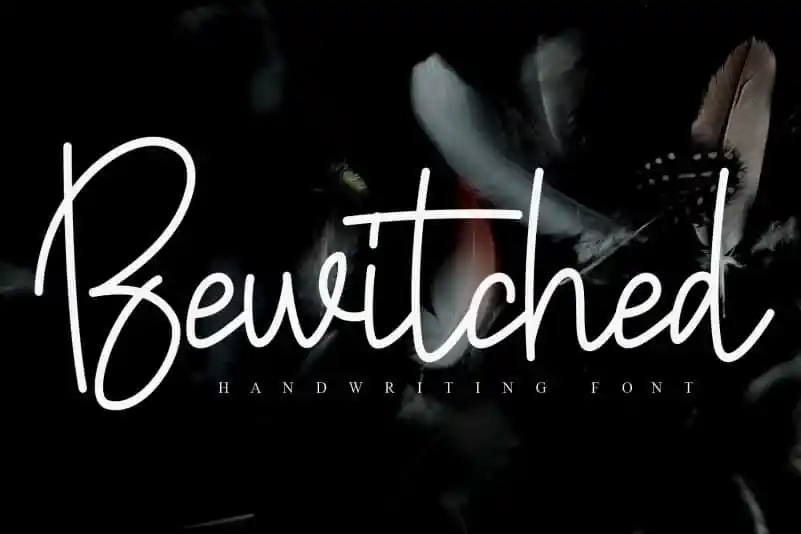
Bewitched Handwritten Font – Download Grátis
Descrição: Através do Bewitched Handwritten Font, a designer creativeletter oferece uma experiência única que vai além das típicas ferramentas de texto padrão. Esta fonte criada sob medida para escrita à mão é não apenas versátil e fácil de usar, mas também capaz de transformar qualquer documento em algo especial e personalizado. Com detalhes cuidadosamente projetados e uma aparente essência única, a Bewitched Handwritten Font traz vida ao seu conteúdo, permitindo que você expressa emoções e sentimentos de formas não tão triviais quanto o uso padrão do texto. Seja para um projeto editorial especial ou apenas para decorar textos pessoais, esta fonte é um elemento indispensável na sua coleção de ferramentas gráficas.